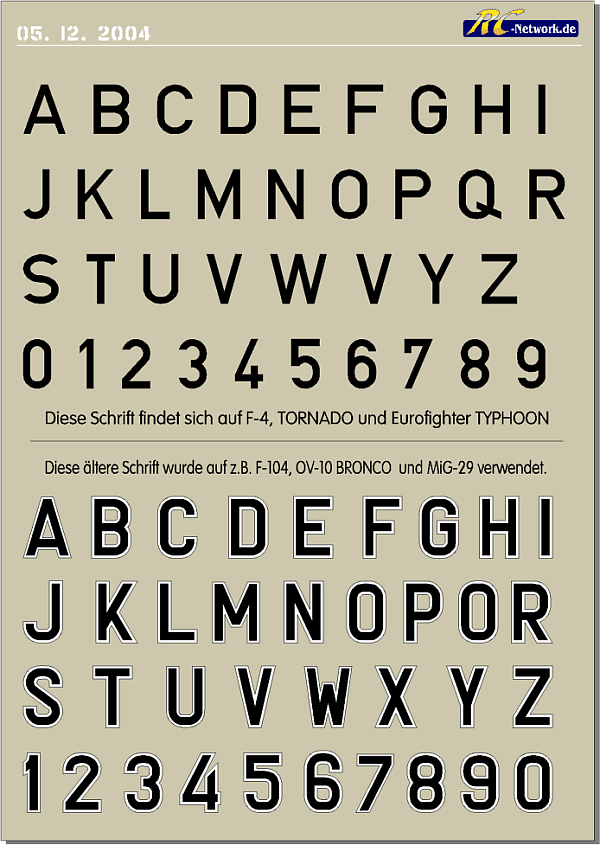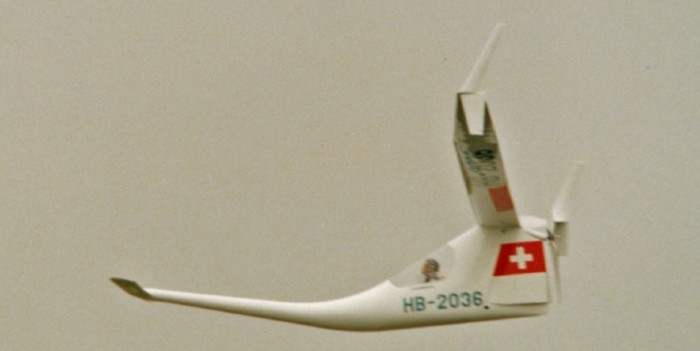
Beschriftung an einem Flugzeugrumpf
Ich suche die Schriftart auf einem Schweizer Experimentalflugzeug.
Weitere Bilder findet man im Internet mit der Suche "Farner Colibri"
Die Schrift ähnelt Arial aber die Ziffer "6" ist bei fast allen Schriften
rundlich während bei der gesuchten Schriftart in der "6" eindeutig eine
gerade Linie auftaucht. Danke für Hinweise.
"Blockschrift für Flugzeuge" wurde da verwendet. Ich würde bei Modellbauvereinen etc. weiterforschen, da wird sicher irgendjemand einen passenden Font haben.